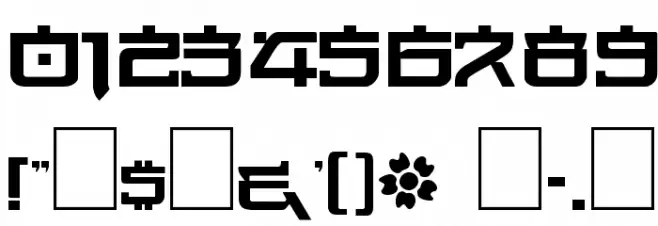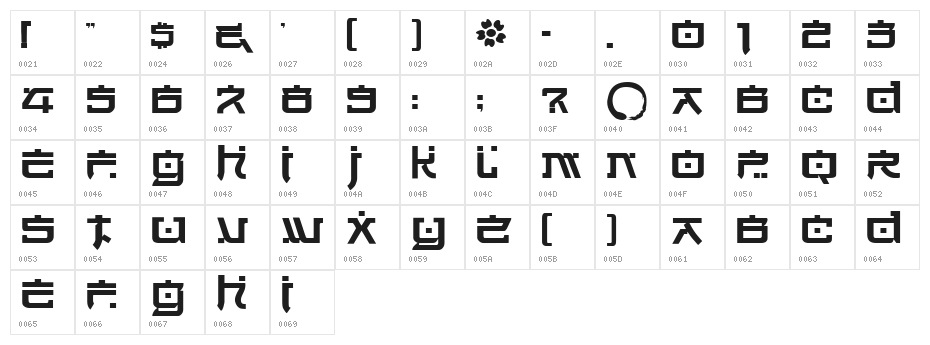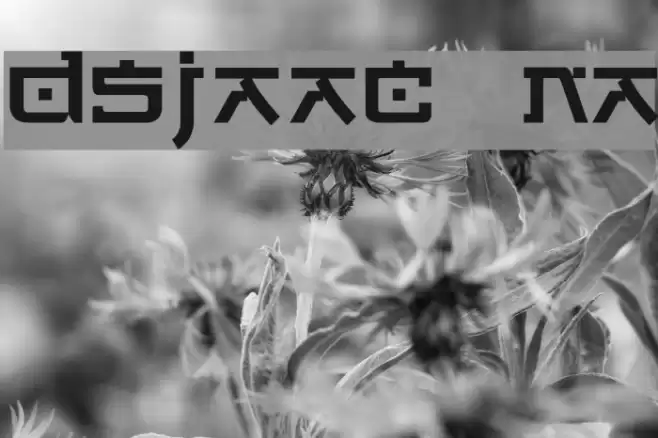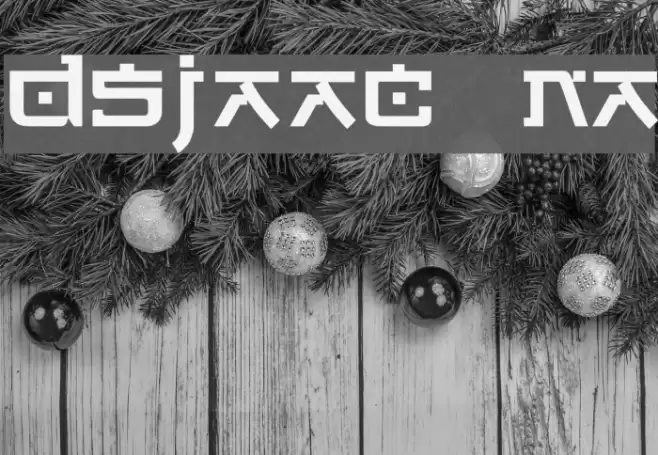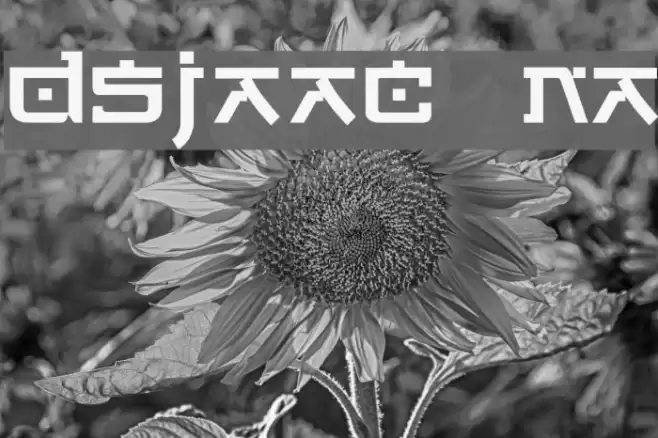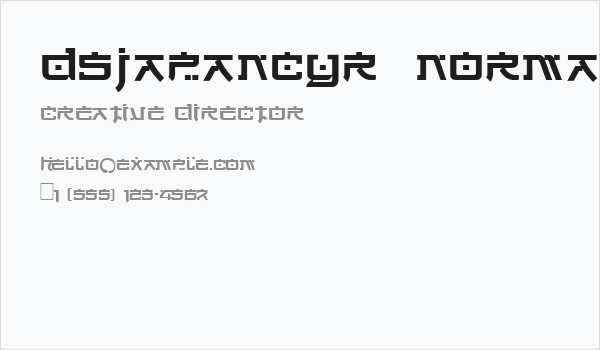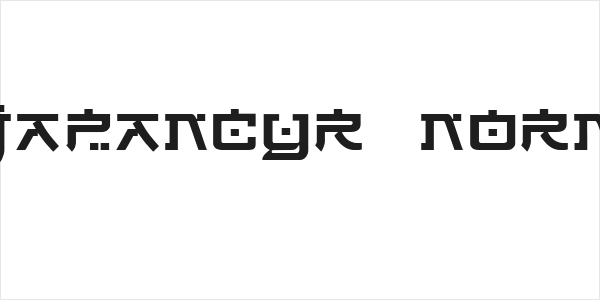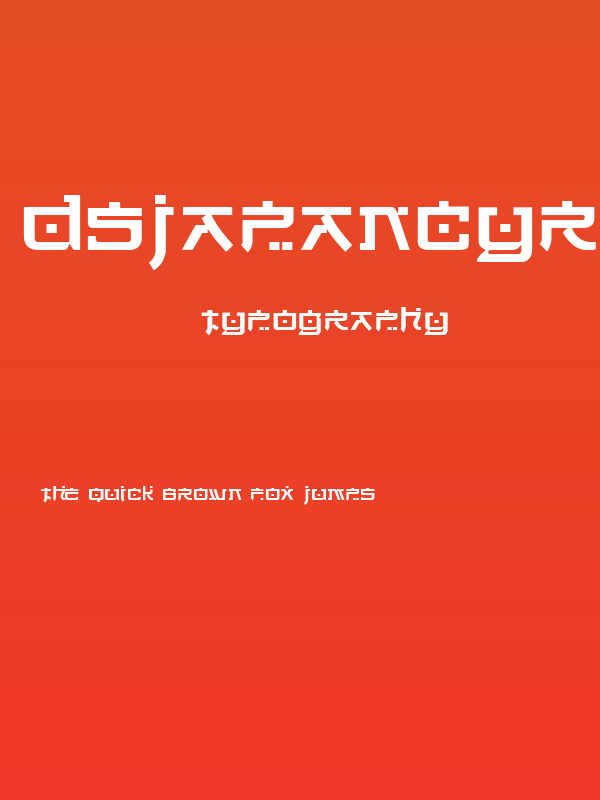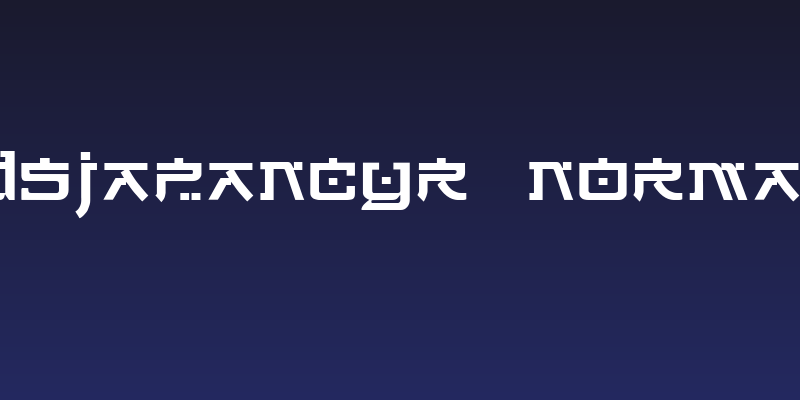
DSJapanCyr Normal Font
| 全体的なスタイル | Futuristic |
| おすすめプロジェクト | Ideal for tech-related branding, sci-fi themed posters, video game titles, and digital interfaces. |